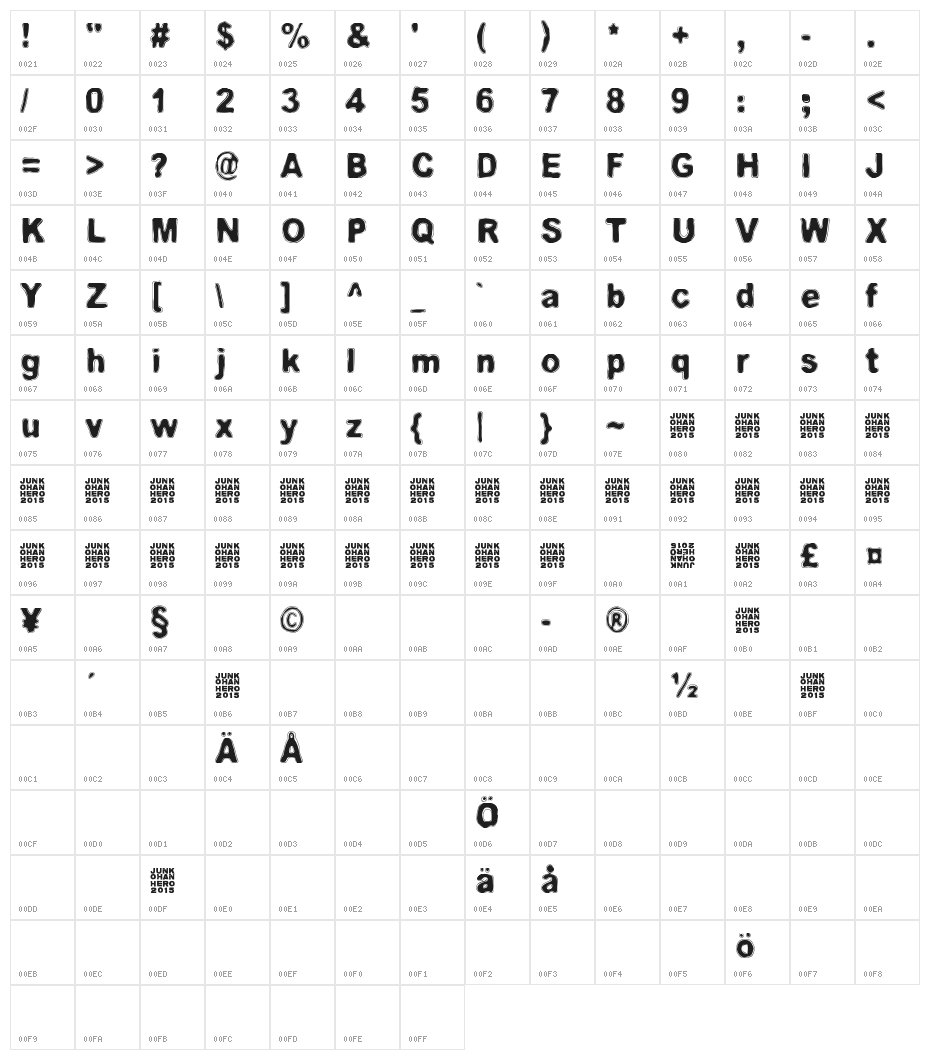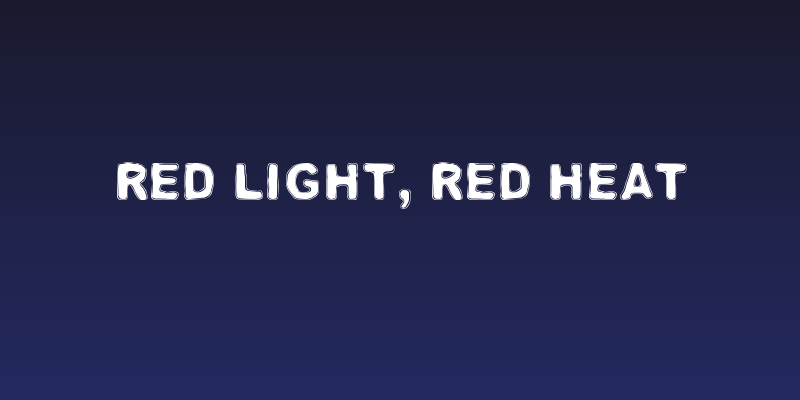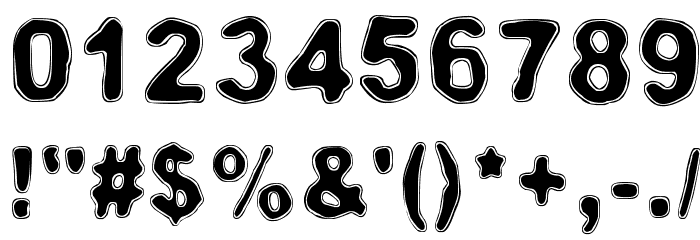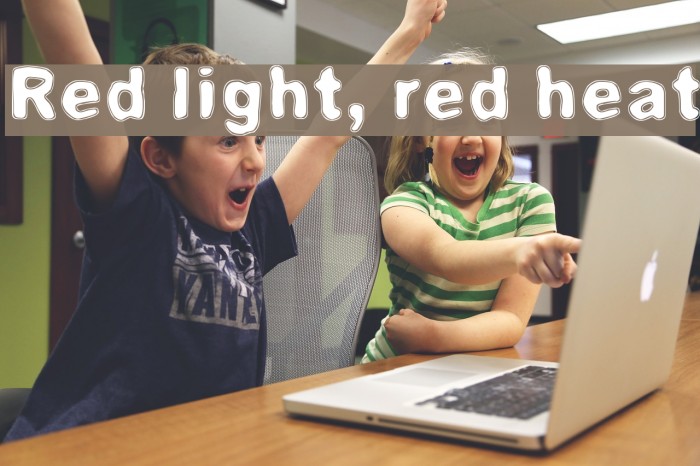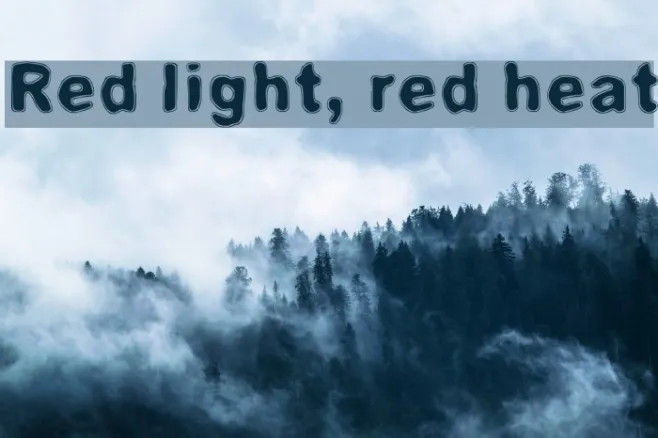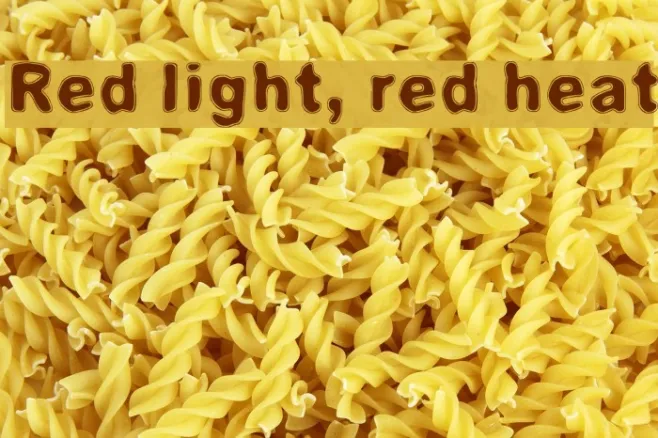
Red light, red heat Font
| Style général | Playful, Whimsical |
| Cas d'utilisation | Headlines, Posters, Branding |
| Projets proposés | Perfect for children's books, playful branding, posters, and any project needing a fun, informal touch. |